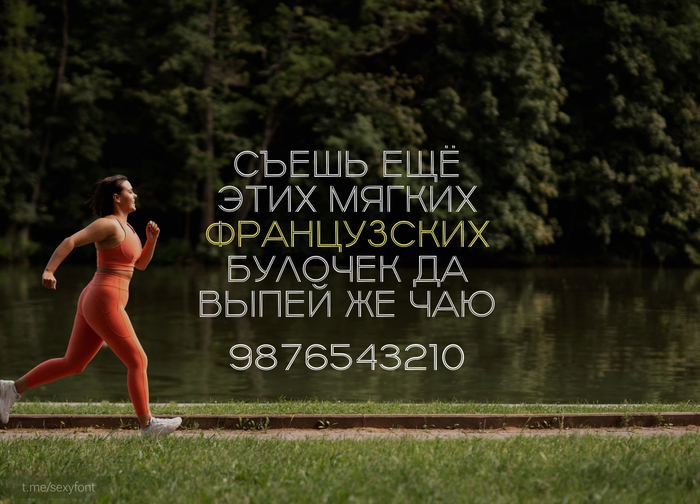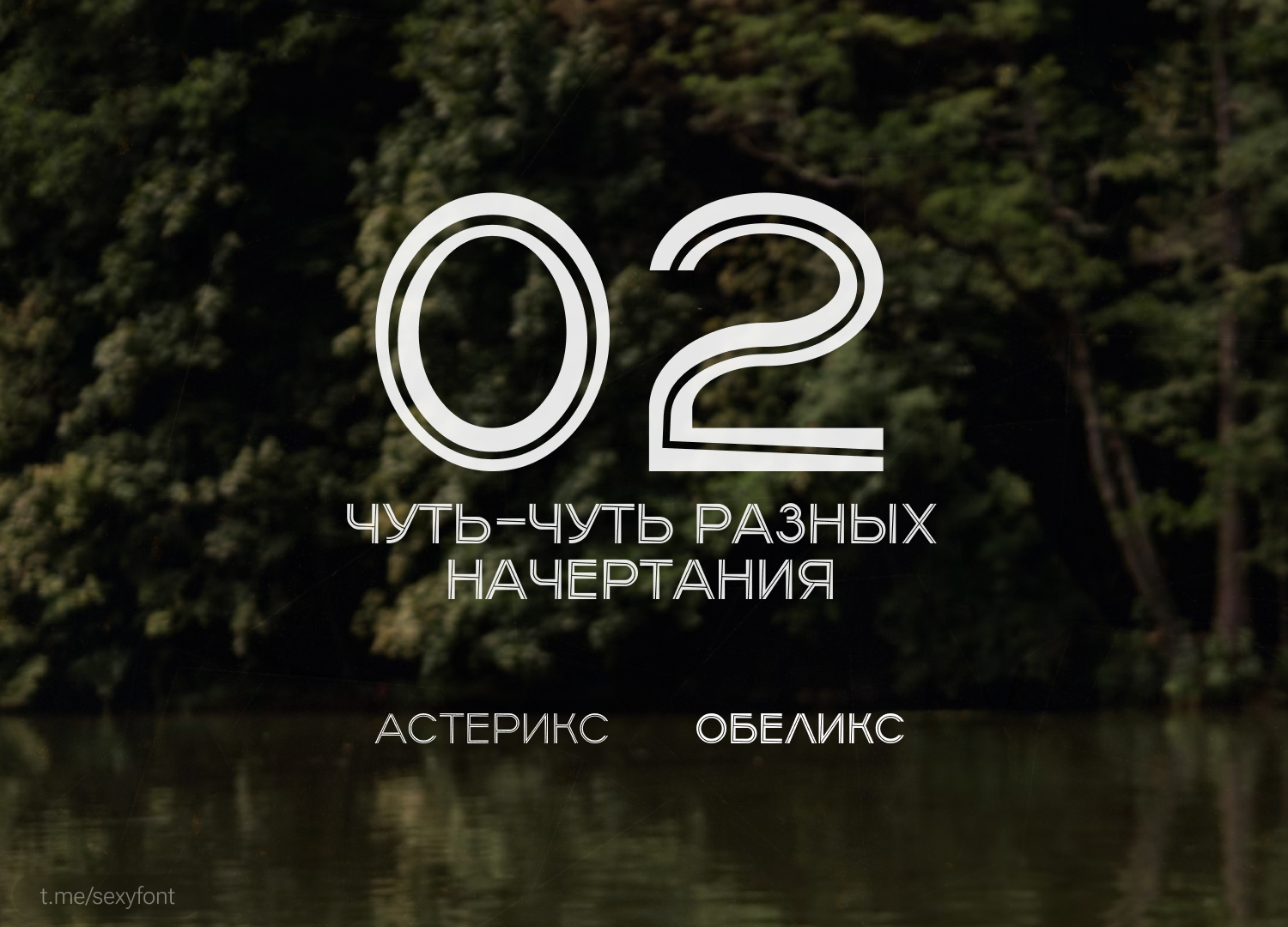
Шрифт Capitellum. Кириллица
Capitellum. Необычный, бесплатный шрифт, естественно с кириллицей. Буквы сделаны в виде контурных линий. Есть даже 2 начертания, потоньше и чуть потолще)